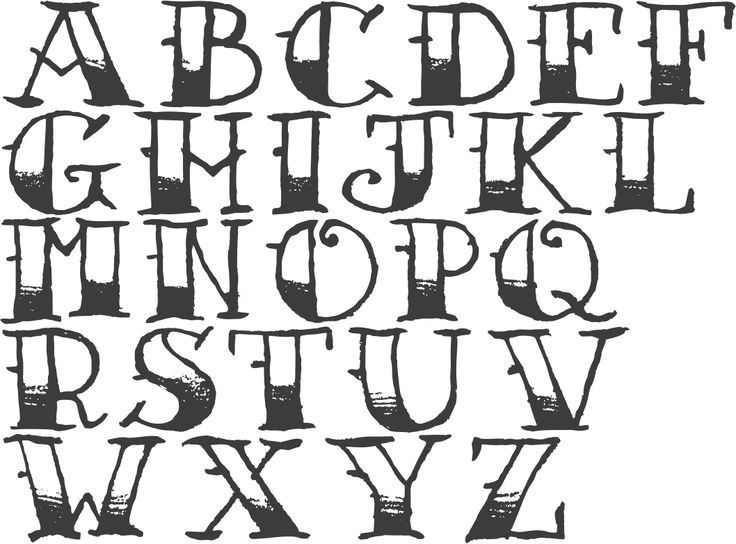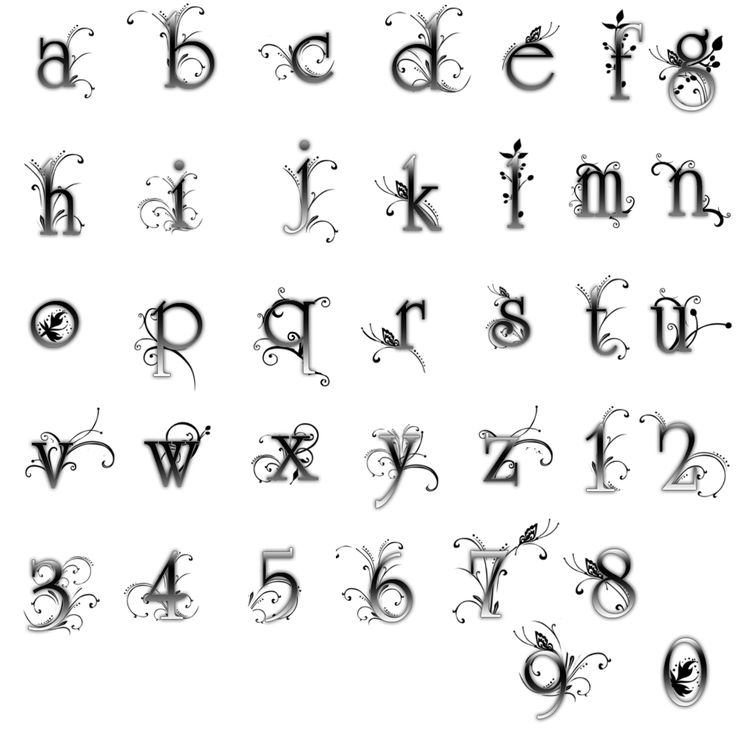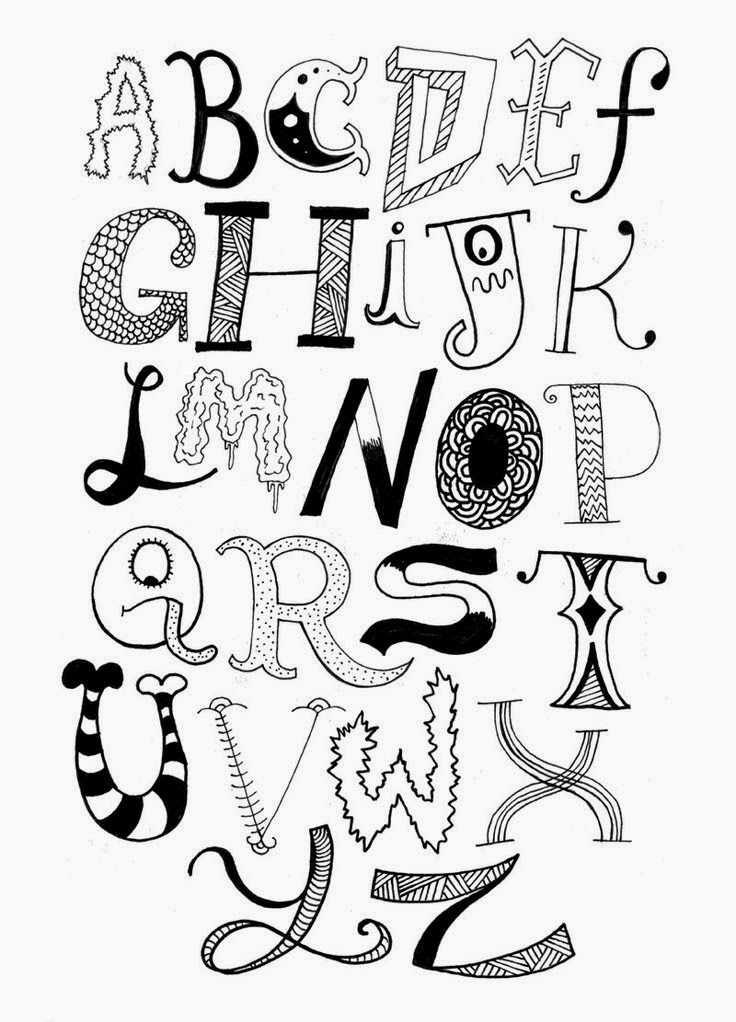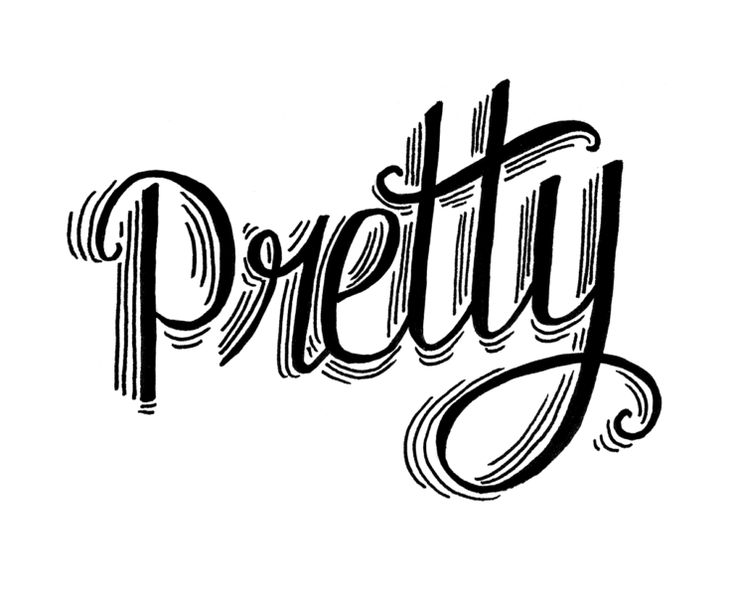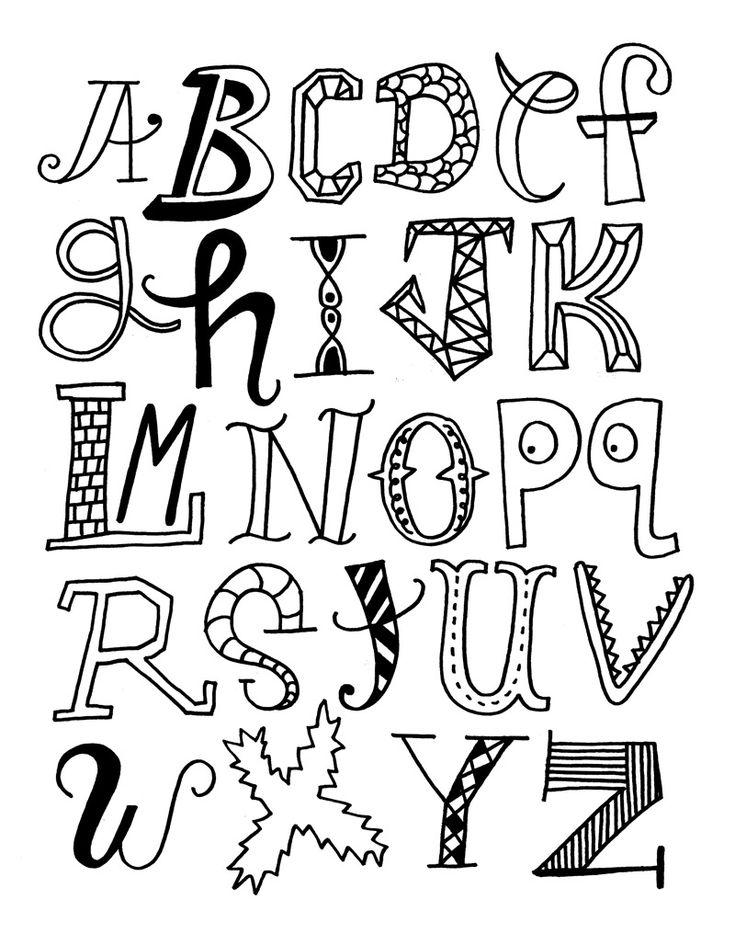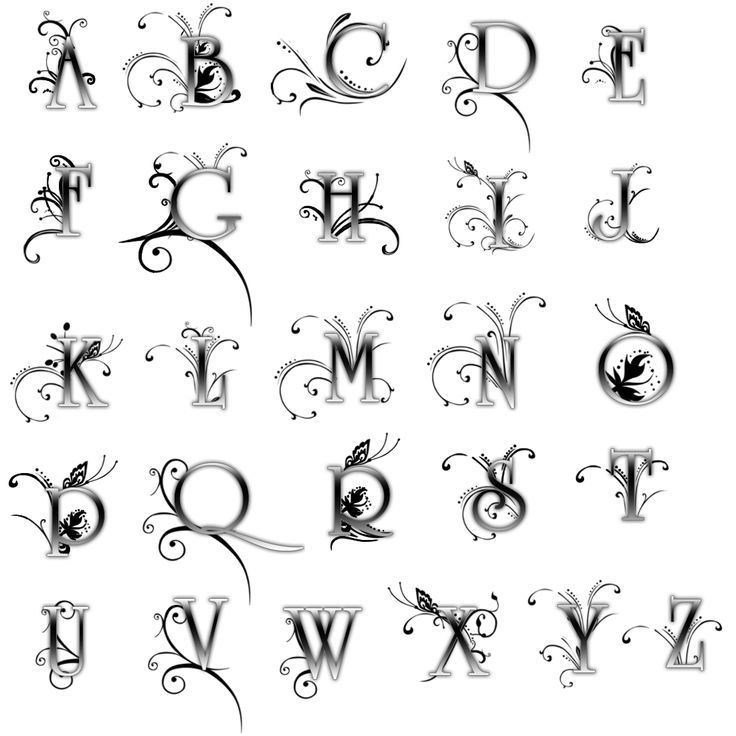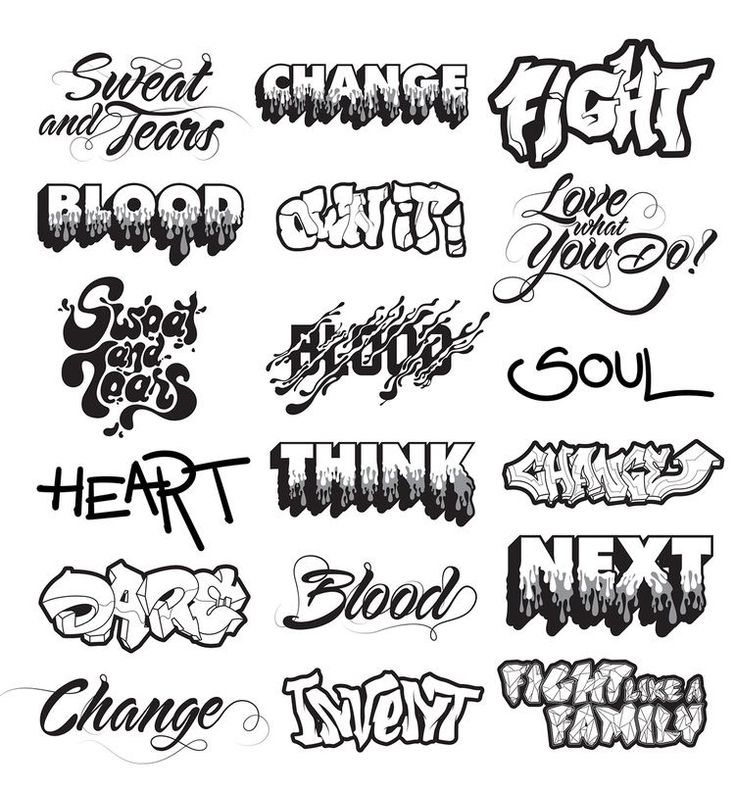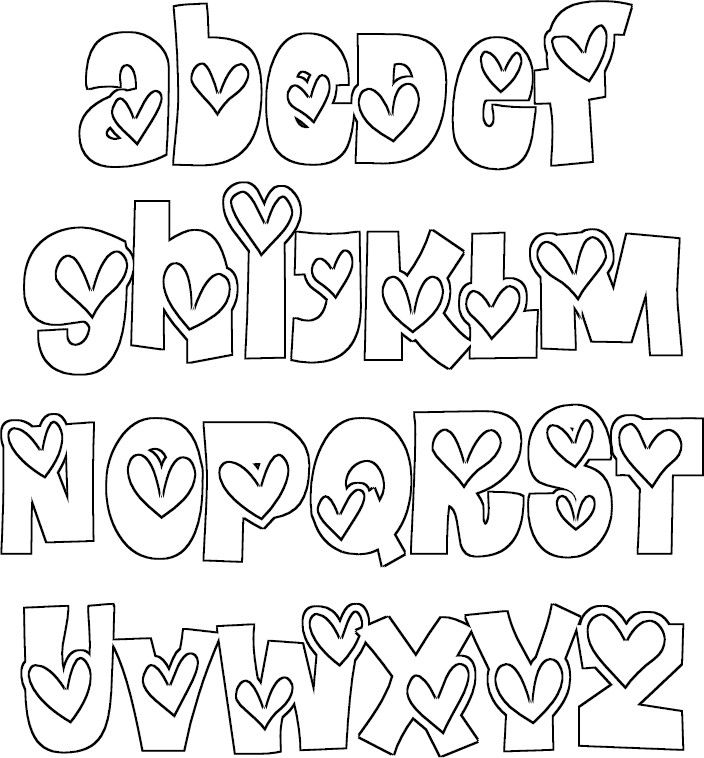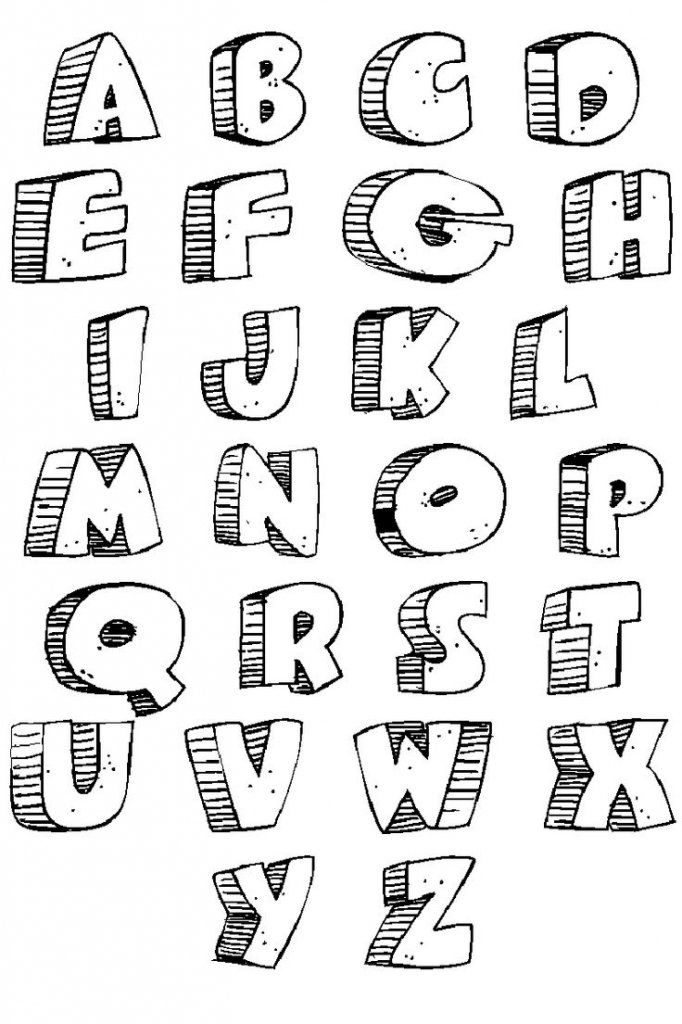
Шрифты нарисованные: Рукописные шрифты | Шрифты Онлайн
49 неоновых шрифтов для создания крутого дизайна
Такие шрифты производят эффект разорвавшейся бомбы. Поиграйте с неоновой типографикой, ведь это лучшая идея, которая могла прийти вам в голову.
Вы тоже заметили, что нас не отпускает “неономания”? Маркетплейсы задыхаются от обилия эффектов, типографики и других ресурсов, которые помогут вам присоединиться к этому сумасшествию.
После успешного выпуска неоновых обоев я понял, что мог бы создать еще больше трендовых проектов, а также показать вам, насколько разнообразными бывают неоновые ресурсы. Поэтому мы представляем вам целую подборку винтажных и современных инструментов: неоновых шрифтов, конструкторов неоновых вывесок, наборов неоновых букв и других бесплатных ресурсов от ключевых платформ и создателей продуктов.
С помощью этих прекрасных визуальных решений вы сможете привлечь внимание людей, не отпугнув их. Мигающие цвета и готовые композиции сделают за вас основную работу — остается лишь подобрать слова, которые будут такими же впечатляющими, как их неоновое оформление.
1. Neon Type — выбор нашей команды ⭐️
Этот профессиональный шаблон Photoshop позволит вам открыть неоновую типографику во всей ее красе. Вы сможете создавать реалистичные вывески, будто состоящие из настоящих неоновых ламп. Мы готовы поспорить, что вы не найдете другой светящийся шрифт, способный конкурировать с этим набором инструментов.
Чтобы вам было удобно кастомизировать надпись, здесь есть многослойные тени и отражения каждого символа, а также буквы в 2 версиях — обычные и включенные. Играйте с неоновыми огнями и ищите то, что больше подходит для вашего проекта.
2. Neonblitz
Представляем вам Neonblitz, уникальный неоновый шрифт в стиле ретро, который поможет вам разрабатывать интересные логотипы. Он вдохновлен настоящими неоновыми вывесками: минималистичные буквы с плавными скругленными углами будто состоят из неоновых трубок. Добавьте в свой проект немного света либо используйте этот шрифт для создания эффектной вывески.
3. Mexcellent
4. Fuse
Fuse — декоративный неоновый шрифт, вдохновленный реальными светящимися вывесками. Геометричные буквы с плавными скругленными углами напоминают настоящие лампы. Этот шрифт идеально будет смотреться на постерах для концертов или фильмов, в журналах, YouTube-видео, логотипах или заголовках.
5. Codeca One
6. Hastron
Hastron — неоновый каллиграфический шрифт, который прекрасно подойдет для оформления приглашений, поздравительных открыток, цитат, создания фирменного стиля, визиток, постеров и многого другого. В комплект входят разные группы альтернативных символов — стилистические и контекстные, декоративные штрихи, лигатуры и сотни других глифов.
Кроме того, шрифт поддерживает PUA Unicode (области частного использования), поэтому вы сможете получить доступ ко всем альтернативным символам без специального программного обеспечения.
7. Beon
8. Rocket Clouds
Перед вами неоновый шрифт, источником вдохновения для которого послужили неоновые огни и музыка 1980-х.
Буквы в стиле ретро оживят ваш дизайн и вызовут у аудитории сильное чувство ностальгии. Rocket Clouds представлен в 2 стилях: Rocket Clouds Regular и Rocket Clouds Alt. Поиграйте с ними, и вы обязательно добьетесь блестящего результата.
9. Neon
10. Neon Desmon
Прописные и строчные буквы, цифры, знаки препинания и неоновые эффекты, которые заставят ваш текст светиться, — в Neon Desmon есть все, что необходимо, чтобы привлечь внимание аудитории. Смело экспериментируйте с этими минималистичными, но эффектными неоновыми буквами — создавайте великолепные вывески для магазинов, элементы фирменного стиля, оформляйте цитаты и заголовки журналов, постеры и многое другое.
11. Neon God
12. Robinson
Robinson — неоновый контурный шрифт, вдохновленный заголовками старых газет. Он отлично подходит для создания смелых привлекательных надписей, за которыми следует текст меньшего размера. Robinson был создан специально для журналов и постеров. Этот светящийся шрифт отлично смотрится в классических неоновых оттенках и включает великолепную наклонную версию.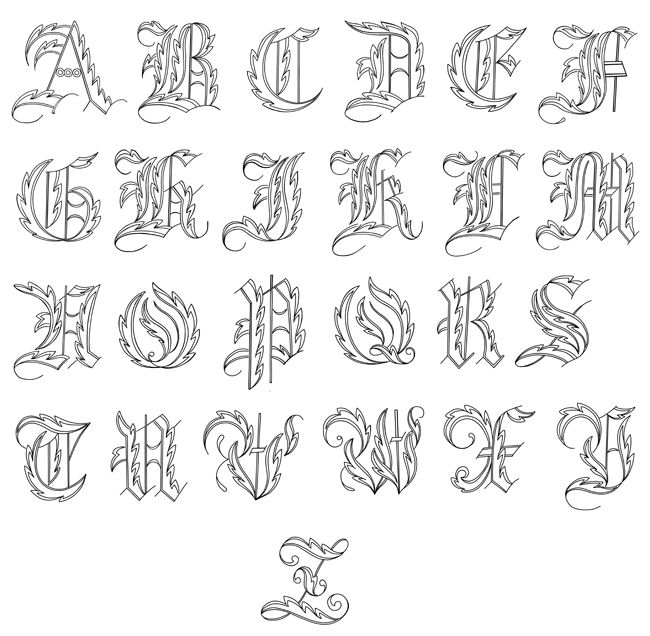
13. NEONEON
14. Gods Own Junkyard
Автор этого неонового шрифта в стиле ретро вдохновлялся творчеством Криса “Неонового человека” Брейси, британского дизайнера, которому принадлежит одна из крупнейших коллекций неоновых вывесок и скульптур.
Gods Own Junkyard состоит из 92 глифов: прописные и строчные буквы, цифры и основные знаки препинания. Этот неоновый шрифт также включает специальный Photoshop-экшен, с помощью которого вы сможете заставить ваш текст светиться.
15. Neon Glow
16. Hitcky
Hitcky совсем не похож на привычные неоновые шрифты, с которыми вы имели дело раньше. Он выглядит современно, свежо и вызывает ассоциации с киберпанком, поэтому, когда мы смотрим на него, у нас не появляется мыслей о неоновых винтажных вывесках или чем-то подобном.
В отличие от семейства шрифтов с засечками, эти нарисованные от руки шрифты выглядели менее серьезными, но они, как правило, придают и передают сильное человеческое прикосновение, где бы они ни применялись.
Шрифты, нарисованные от руки, трудно поддерживать сами по себе, но они идеально подходят для следующих ситуаций:
1. Веб-сайты, нарисованные от руки
Если вы хотите придать своему новому веб-дизайну эскизный или нарисованный от руки вид, эти шрифты, без сомнения, идеально подходят для макета. Нажмите здесь, чтобы увидеть больше примеров веб-сайтов в рисованном стиле.